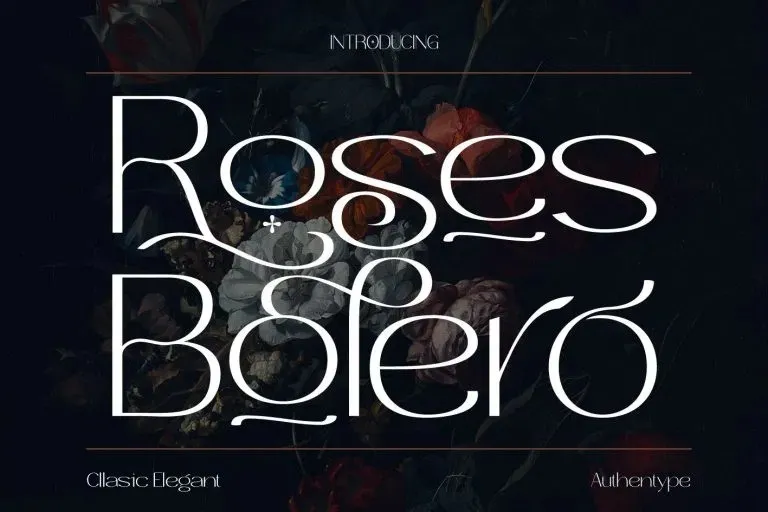
Roses Bolero Sans Serif Font – Fonte Grátis
Roses Bolero Sans Serif Font – Download Grátis
Roses Bolero Sans Serif Font
Roses Bolero Sans Serif é uma fonte moderna e elegante que traz aos profissionais de design um recurso versátil para seu trabalho. Com sua estética única, Rosa Bolero oferece todo o conjunto necessário de letras maiúsculas e minúsculas, símbolos multilíngues, números, pontuação e ligaduras. Essa fonte elegante é perfeita para aplicações em cartazes, revistas ou qualquer projeto que exija uma identidade visual sofisticada com um design florido no asterisco. Perfeito para conceitos de beleza e design estiloso, Rosa Bolero está ideal para trabalhos como essas. Seja em seu layout elegante de poster, sua capa sofisticada de revista ou para o branding da marca, Rosa Bolero é uma escolha perfeita para quem busca uma combinação moderna e charmosa que se destaca. Sempre presenteando um design floral nos asteriscos, Rosa Bolero ajuda a criar um visual impecável e memorável, ideal para qualquer aplicação visual de alta qualidade no mundo do design gráfico.